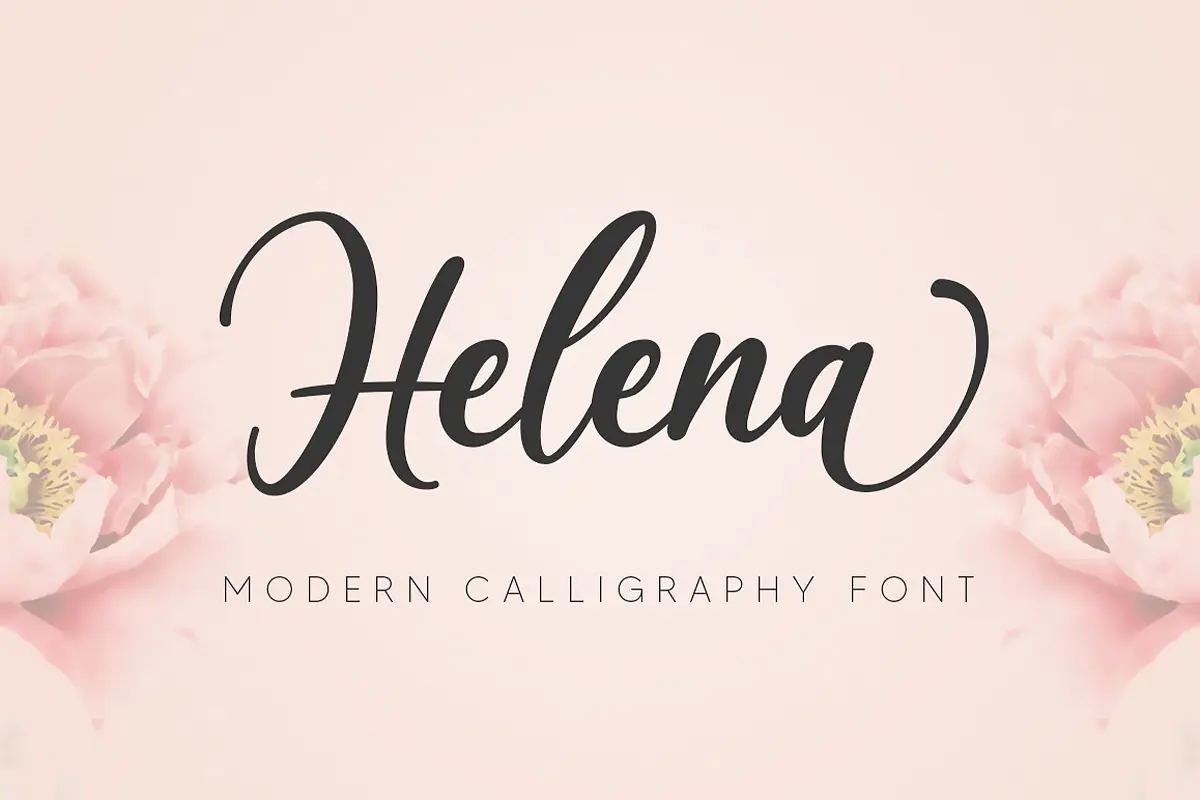
فونت دستنویس شیک و ظریف
فونت Helena یک فونت اسکریپت (Script Font) شیک و ظریف است که حس شکوه، ظرافت و اصالت را در نوشتههای شما به نمایش میگذارد. طراحی این فونت با لیگاتورها و آلترنیتهای زیبا همراه است و آن را به انتخابی بینقص برای پروژههایی تبدیل میکند که نیاز به استایل هنری و لوکس دارند.
- سبک: فونت اسکریپت شیک و ظریف
- طراحی مدرن، ظریف و چشمگیر
- دارای آلترنیتها و لیگاتورهای استایلیش
- مناسب برای پروژههای چاپی و دیجیتال
- طراحی لوگوهای لوکس و برندهای مد
- ساخت دعوتنامههای رسمی و مراسمهای خاص
- استفاده در پوسترها و کارتهای عاشقانه و هنری
- افزودن به پورتفولیو طراحان برای نمایش سبکهای اسکریپت ظریف